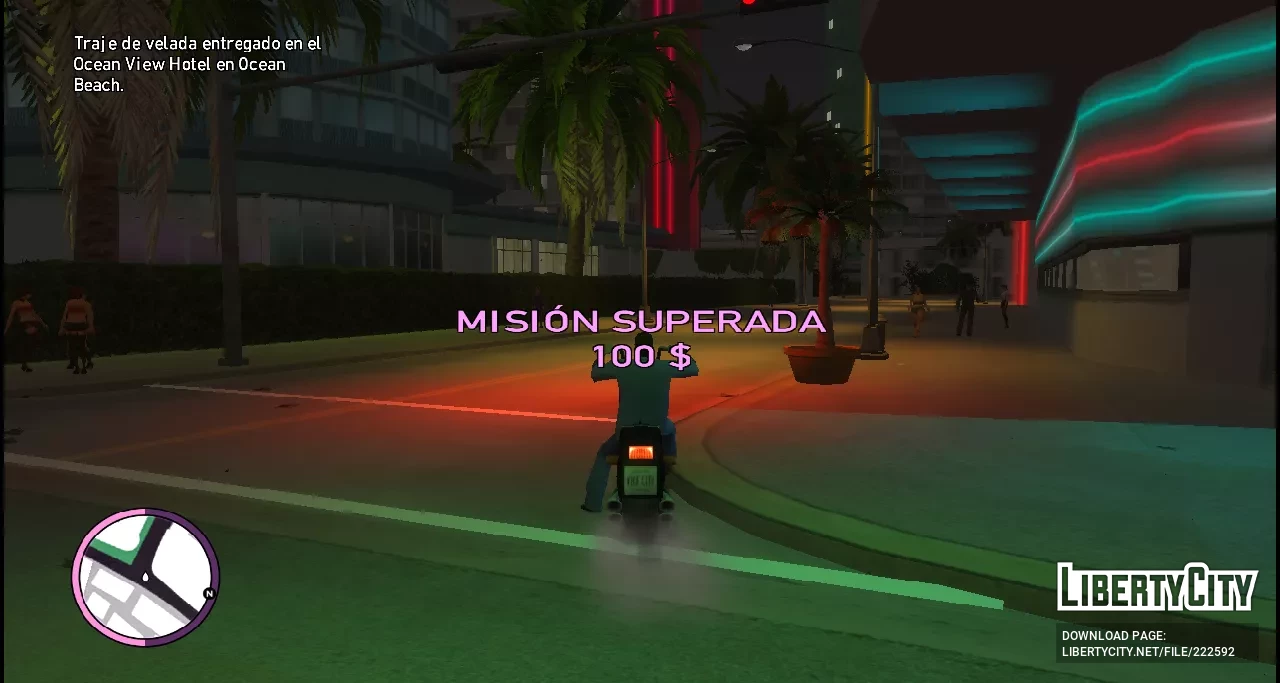
Новые шрифты, более приближённые к оригиналу
Новые шрифты, более приближённые к оригиналу для Vice City Nextgen Edition
С этим модом вы получите шрифты из оригинальной GTA Vice City, а также несколько исправлений по сравнению с предыдущей версией.
Особенности мода:
- Исправлены размеры некоторых букв и цифр — теперь они не сливаются и читаются чётче.
- Добавлена тень за числами денег и патронов, как в оригинальной Vice City — улучшена видимость.
- Звёзды розыска теперь окрашены в синий цвет, как это было в Vice City на консолях.